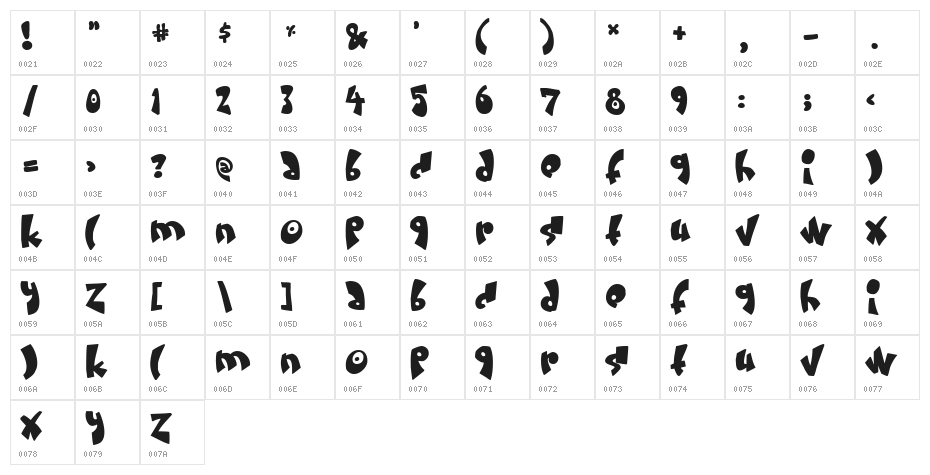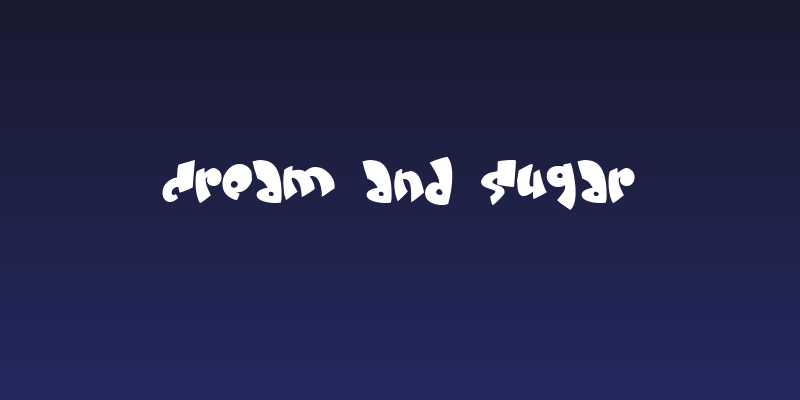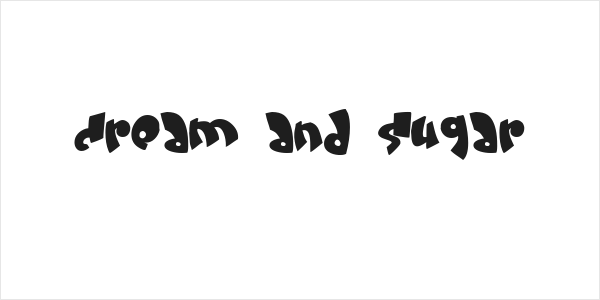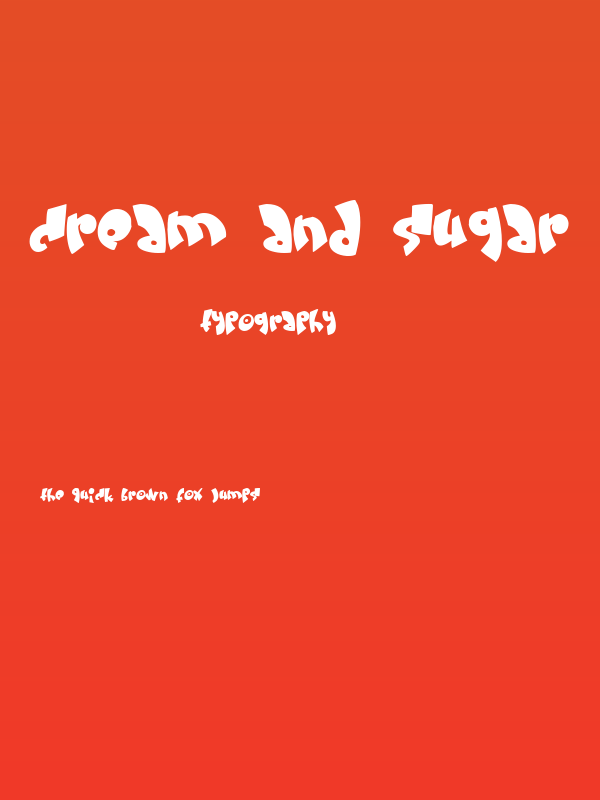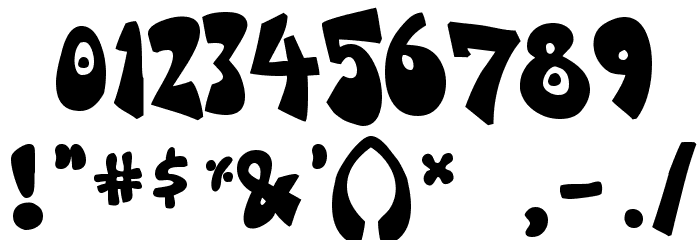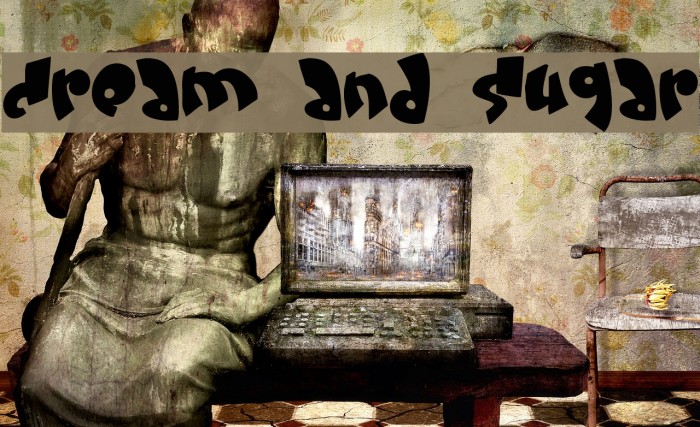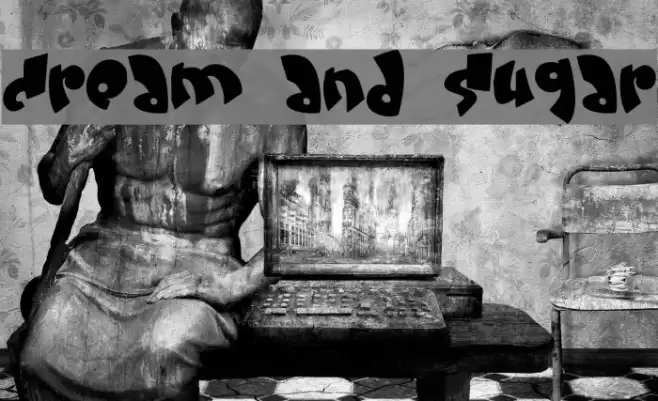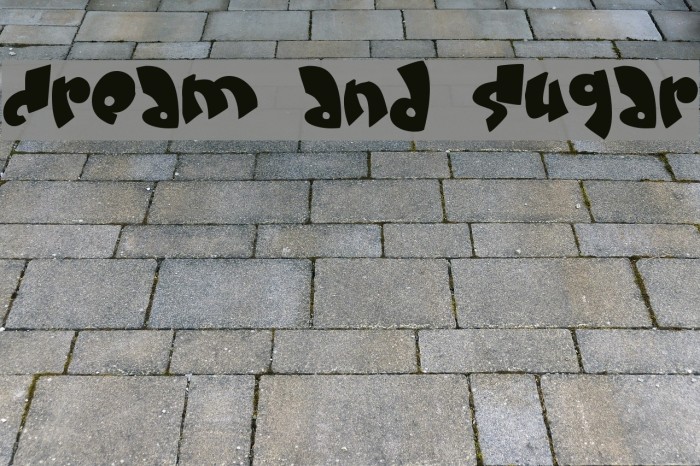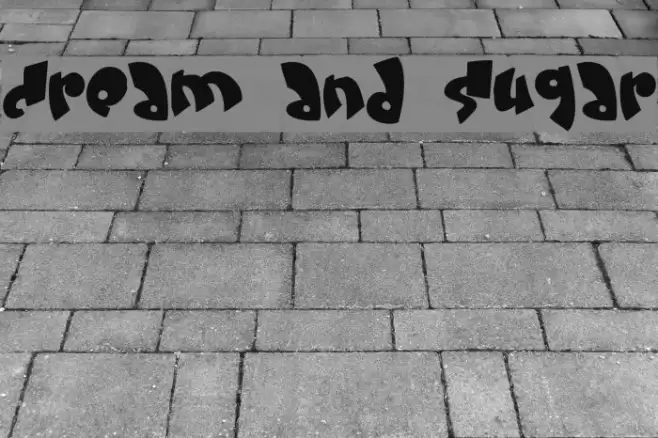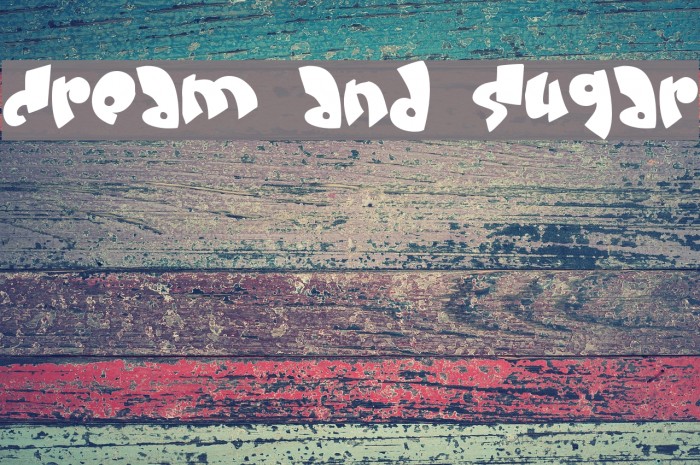
Cream and sugar Font
| Estilo general | Playful |
| Proyectos propuestos | Ideal for children's books, playful branding, party invitations, and creative posters. |